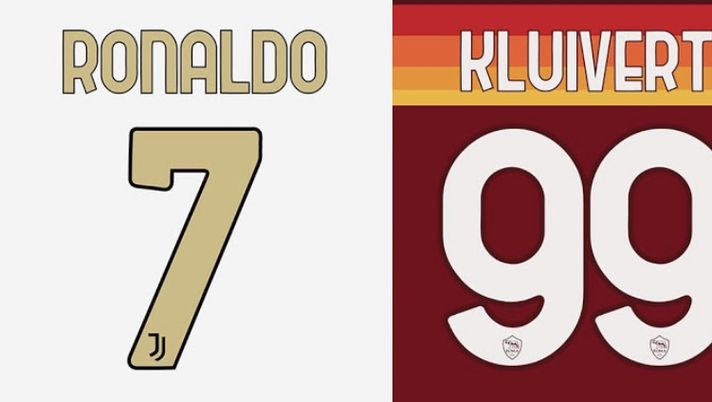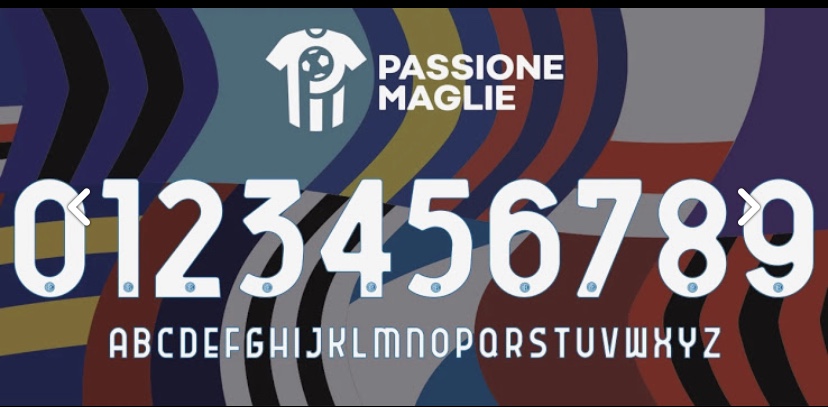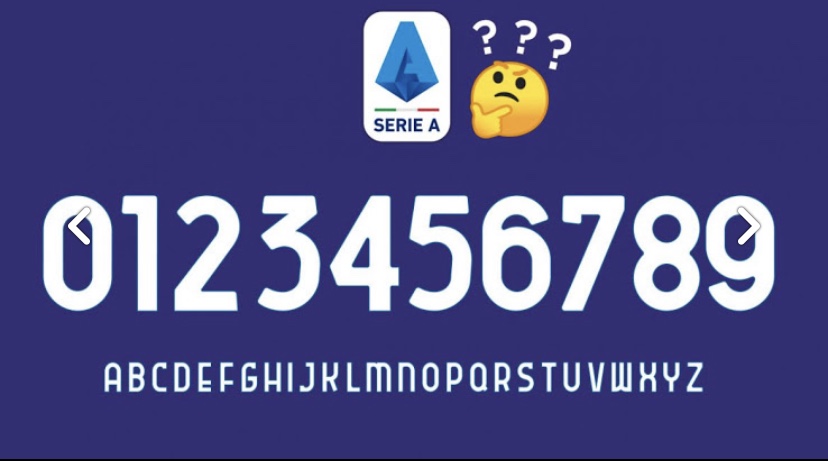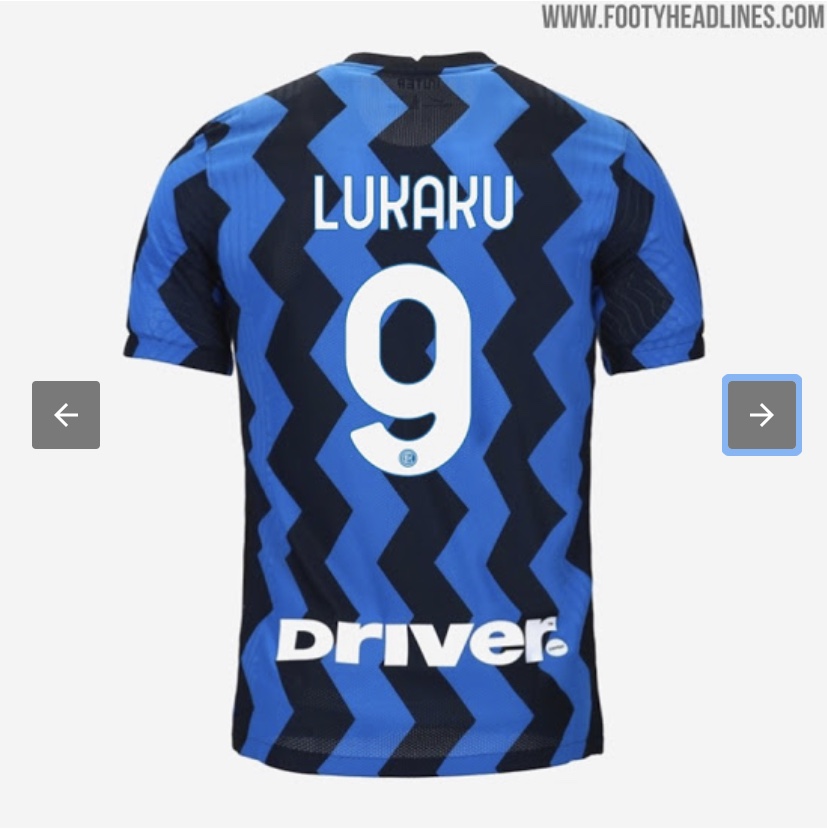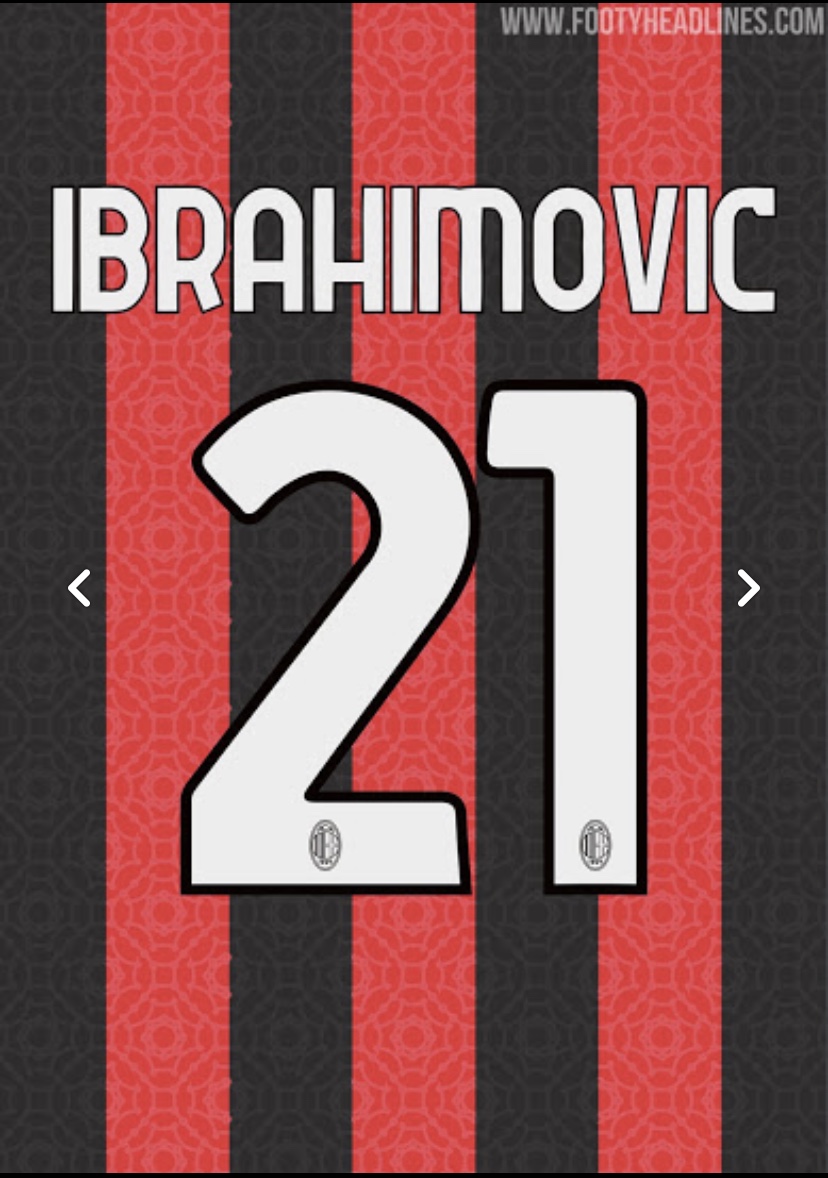
ULTIME NOTIZIE SERIE A - Dalla prossima stagione, 2020-2021, il font di numeri e nomi sulle maglie di Serie A sarà uguale per tutte le 20 squadre del torneo
ULTIME NOTIZIE SERIE A - Dalla prossima stagione, 2020-2021, il font di numeri e nomi sulle maglie delle 20 squadre di Serie A sarà uguale per tutti.
Una scelta che segue quella di altre leghe, quali, ad esempio, la Premier League, per dare coerenza nello stile delle divise ed una migliore leggibilità di nome e numero tanto allo stadio quanto alla televisione.
Il noto portale web 'FootyHeadlines' ha anticipato quale dovrebbe essere il font, grazie anche al lavoro del sito 'Passione Maglie' e come potrebbero apparire i nomi di alcuni calciatori nella prossima stagione.
Differentemente dal campionato inglese, e come accade invece con la Liga, nella parte bassa dei numeri ogni club di Serie A potrà inserirà il proprio logo.